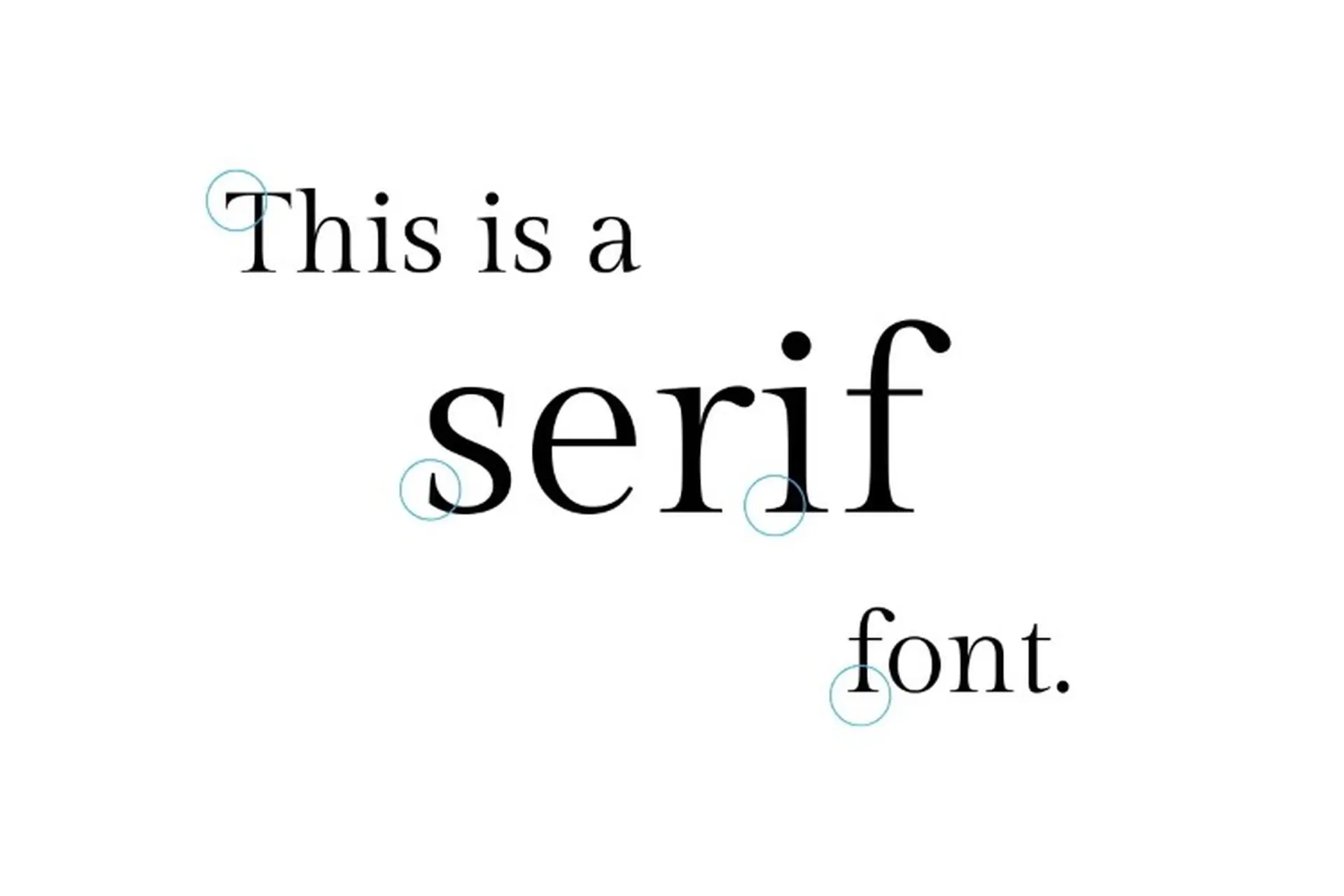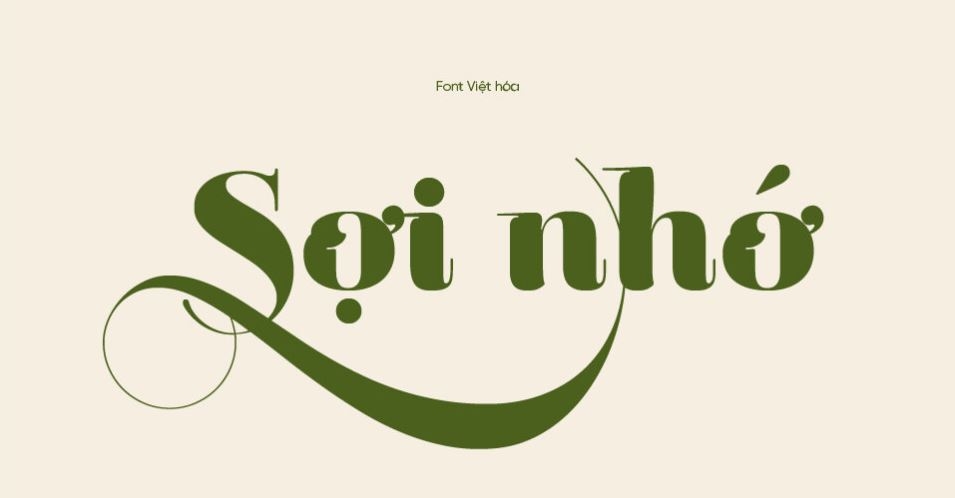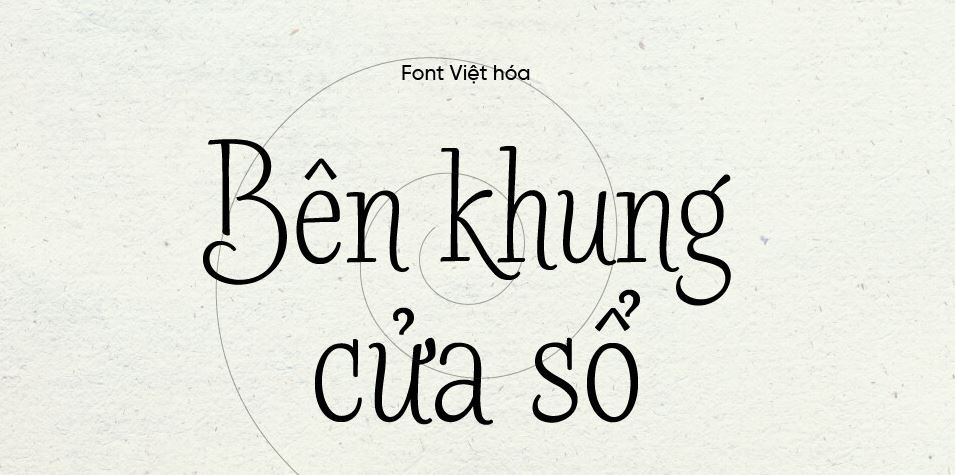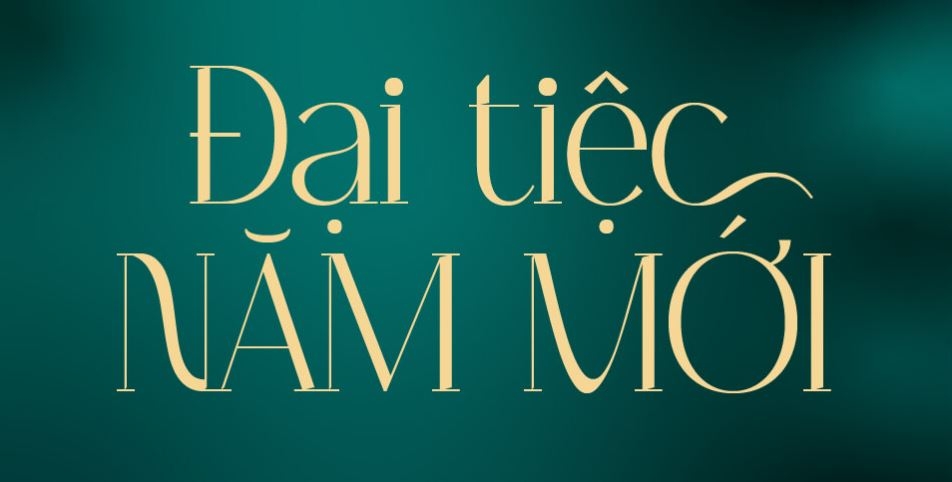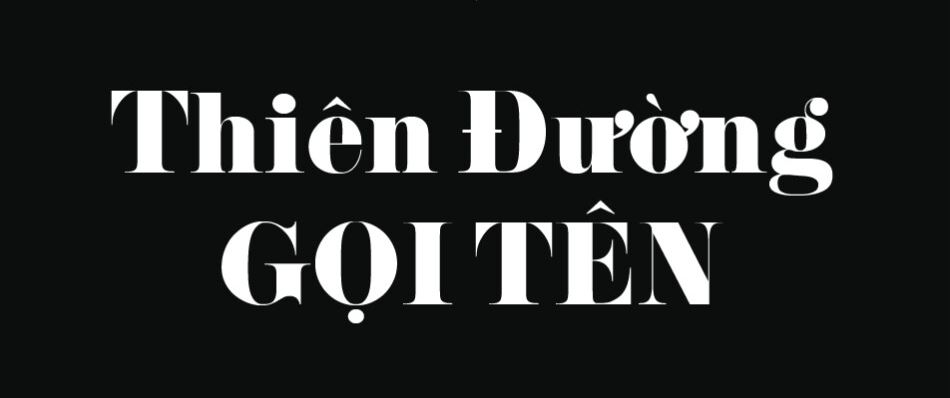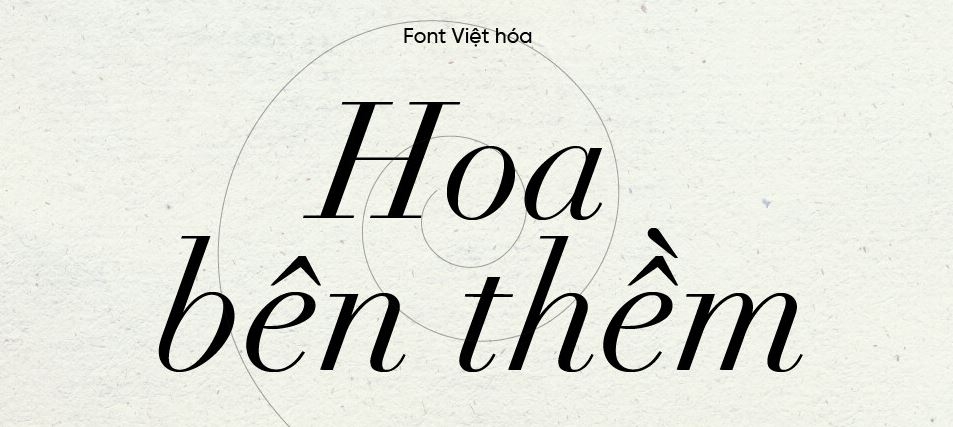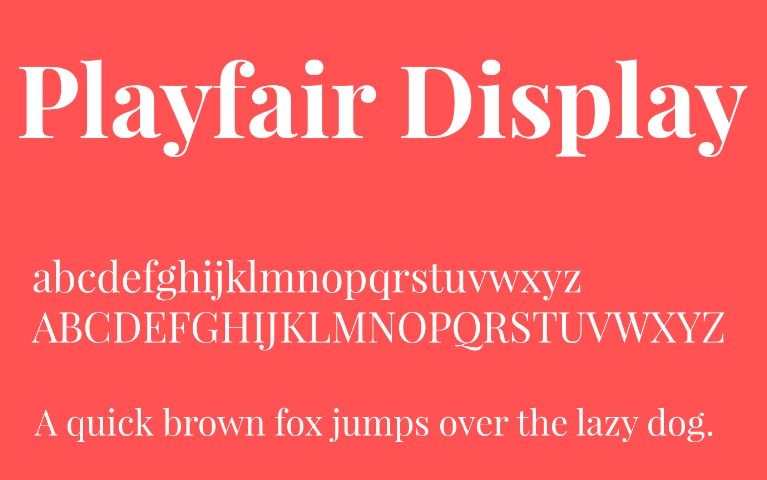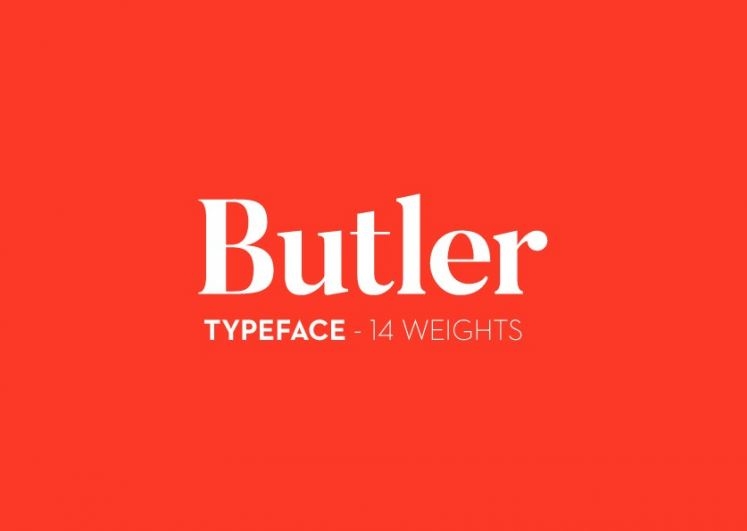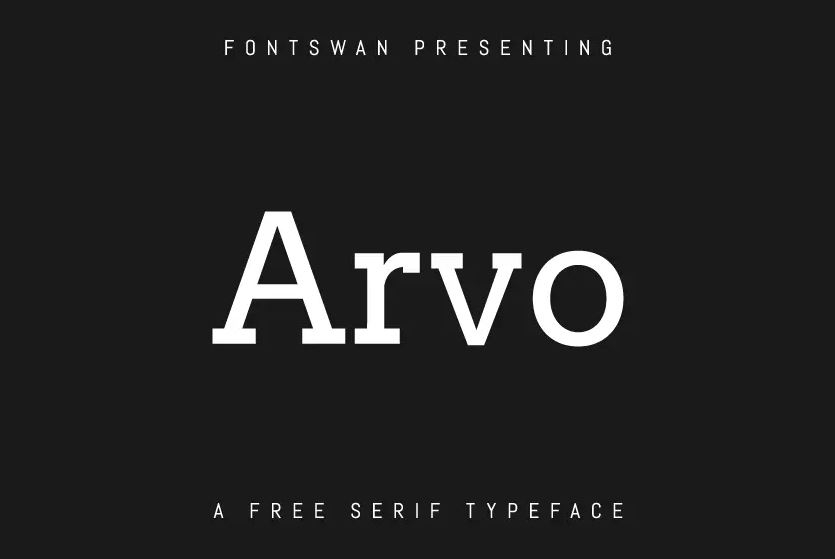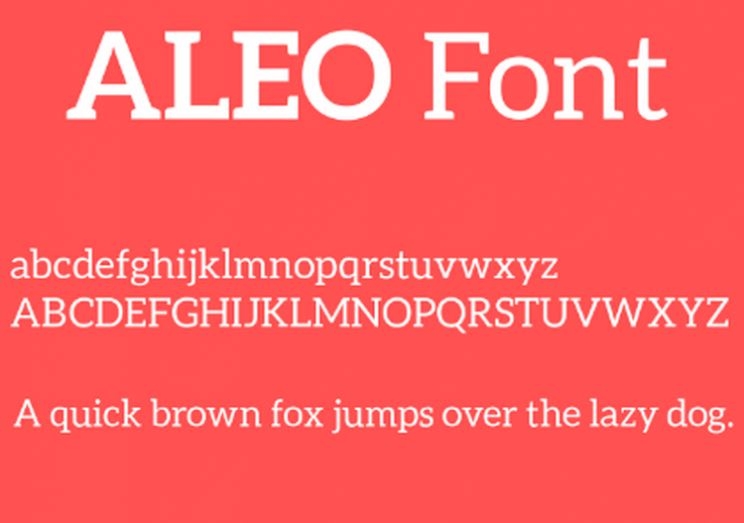
Tổng hợp 15 font chữ có chân đẹp mang đậm nét cổ điển, sang trọng được designer sử dụng nhiều
Font chữ có chân hay còn gọi là font chữ Serif mang đậm vẻ đẹp cổ điển, sang trọng và được sử dụng rộng rãi trong nhiều lĩnh vực như thiết kế đồ họa, xây dựng website, in ấn,... Dưới đây là 15 font chữ có chân đẹp được FPT Shop tổng hợp. Mời bạn tham khảo nhé!
Với vẻ đẹp sang trọng, mang nét cổ điển, font chữ có chân trở thành lựa chọn hàng đầu, thu hút sự chú ý của người yêu thiết kế. Bài viết này sẽ giới thiệu đến bạn đọc 15 font chữ có chân đẹp và nổi bật được nhiều người sử dụng.
Font chữ có chân là gì?
Font chữ có chân là loại phông chữ có đường chân hoặc nét nhỏ được thêm vào các thành phần của chữ cái. Đường nét này có tác dụng ổn định cho cấu trúc chữ cái giúp tạo ra một diện mạo trang trọng và cổ điển cho văn bản. Do đó, font chữ có chân được sử dụng khá rộng rãi bởi các nhà thiết kế website, thiết kế quảng cáo, logo hay nhân viên văn phòng thường xuyên soạn thảo văn bản.
Liệt kê 15 mẫu font chữ có chân phổ biến nhất
Trong bộ font chữ này, các mẫu thiết kế đều có đặc điểm chung là bố cục rõ ràng và có tính ứng dụng cao. Bạn có thể tham khảo 15 mẫu thiết kế font chữ có chân phổ biến nhất hiện nay.
1. Reina
font chữ có chân 01
Font chữ Reina dễ đọc, kích thước nhỏ gọn giúp tiết kiệm không gian trên bề mặt sử dụng trong các tài liệu. Điểm nhấn quan trọng của font Reina là việc tạo ra sự tương phản rõ rệt giữa các nét chữ để người nhìn dễ dàng phân biệt và nhận diện ký tự. Với nhiều loại chữ khác nhau, từ đơn giản đến phức tạp, từ cổ điển đến hiện đại, font chữ Reina có tính ứng dụng cao như viết thư pháp, thiết kế đồ họa hay sử dụng trong trang web, ứng dụng di động,…
2. Barmbrack
font chữ có chân 02
Font chữ có chân Barmbrack được lấy cảm hứng từ phong cách showcard lettering với các đường nét đậm, phóng khoáng và các phần chân chữ được cách điệu. Nét chữ trong thiết kế có độ dày lớn tạo cảm giác mạnh mẽ và ấn tượng. Đường gạch chân dưới mỗi chữ biến thể thành các hình dạng khác nhau đem lại cảm giác vui tươi và độc đáo. Với những đặc điểm nổi bật này, việc ứng dụng font chữ trong các tiêu đề của web, poster quảng cáo sẽ thu hút sự chú ý của mọi người.
3. Tropical Qebalon
font chữ có chân 03
Font Tropical Qebalon là sự kết hợp giữa tính mềm mại và tinh tế trong từng nét chữ. Độ dày mỏng của đường nét tạo nên chất lãng mạn và hoài cổ cho mọi tác phẩm thiết kế. Với hình ảnh mượt mà và độc đáo, font Tropical Qebalon sẽ là lựa chọn tuyệt vời cho các dự án thiết kế mang tính nghệ thuật, sáng tạo và cá nhân hóa. Đây không chỉ là một font chữ đơn thuần mà còn là một tác phẩm nghệ thuật độc đáo mang lại cảm giác mới mẻ và tinh tế cho người sử dụng.
4. Sreda
font chữ có chân 04
Sreda là một font chữ khác biệt hẳn so với các loại font chữ khác bởi các đường nét dày và đậm hơn. Các chân chữ của Sreda được thiết kế dày và chắc chắn mang đến cảm giác vững chãi và ổn định. Sreda rất hiệu quả trong việc gây sự chú ý của người dùng và tạo nên sự độc đáo cho thiết kế. Đặc biệt, Sreda thường được sử dụng trong các tiêu đề, banner và các đoạn văn bản nổi bật góp phần tạo sự nổi bật cho thiết kế.
5. Yeseva One
font chữ có chân 05
Yeseva One có đường nét mảnh mai và thanh lịch tạo nên một cảm giác khá cổ điển và lịch sự. Những đường cong của chữ cái được vẽ tỉ mỉ mang lại nét tinh tế và quý phái. Các chân chữ của font Yeseva One được cách điệu tạo cảm giác thú vị và tự do cho dáng chữ. Font thường được sử dụng trong các dự án thiết kế đồ họa bao gồm thiệp cưới, bìa sách, logo và các ứng dụng nghệ thuật khác.
6. Pistilli
font chữ có chân 06
Những đường nét của font chữ có chân Pistilli đều rất thanh lịch khiến bạn cảm nhận được nét tinh tế và lãng mạn. Các chân chữ Pistilli cũng được thiết kế rất mảnh, vừa độc đáo vừa cuốn hút. Font chữ Pistilli thích hợp sử dụng trong các thiết kế đòi hỏi sự sang trọng và tinh tế như thiệp cưới, quảng cáo hoặc tiêu đề tạp chí.
7. Balerga
font chữ có chân 07
Cách bố trí và thiết kế kiểu chữ của Balerga mang nét cổ điển và cao cấp. Font này thường được sử dụng trong các thiết kế đòi hỏi sự trang trọng và nổi bật. Các đường nét đậm và chân chữ dày tạo nên sự ổn định và độ bền cho font chữ phù hợp để sử dụng trong các tiêu đề lớn hoặc các phần chú thích. Ngoài ra, Balerga còn được sử dụng để sáng tạo các logo hoặc bất kỳ thiết kế nào mà bạn muốn có ấn tượng mạnh mẽ và sang trọng.
8. Adventure
font chữ có chân 08
Font chữ Adventure là một loại font chữ có các đường kẻ ở đáy các ký tự giúp người nhìn thấy được sự mạnh mẽ và mạo hiểm. Bằng cách sử dụng font chữ này, người thiết kế có thể truyền tải được tính chất phiêu lưu, khám phá và hành động của một thông điệp nào đó. Font này thích hợp cho các thiết kế liên quan đến du lịch, thám hiểm, thiên nhiên hoang dã hoặc những hoạt động ngoài trời.